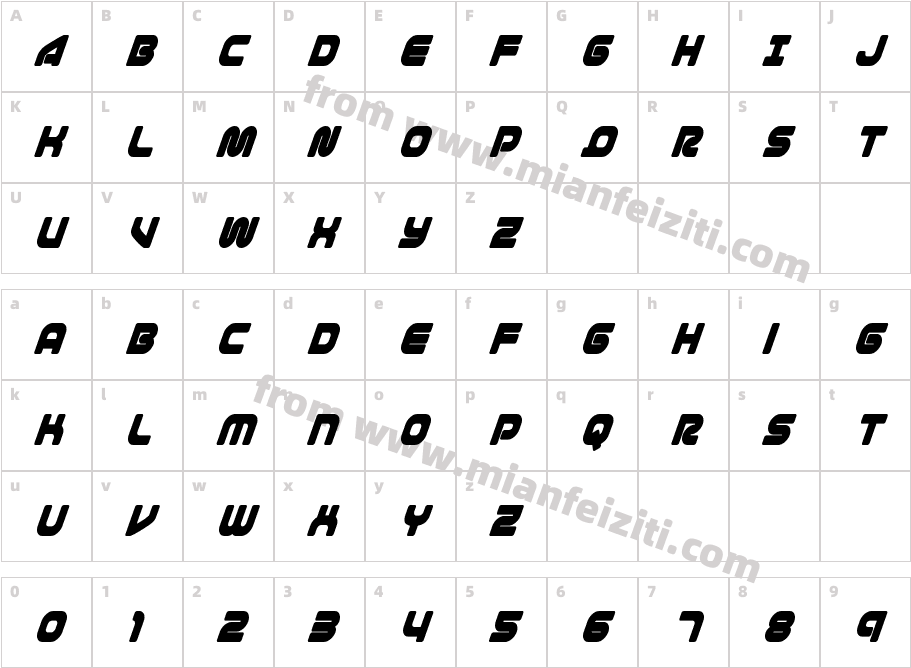
1st Enterprises Condensed Super Italic
字体名称: 1st Enterprises Condensed Super Italic
Postscript名称: 1stEnterprisesCondensedSuper-Italic
字体版本: Version 1.0; 2017
字体字重: Condensed Italic
1st Enterprises Condensed Super Italic预览图1
1st Enterprises Condensed Super Italic预览图2
1st Enterprises Condensed Super Italic字体映射图